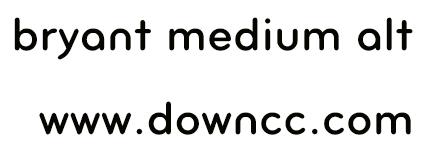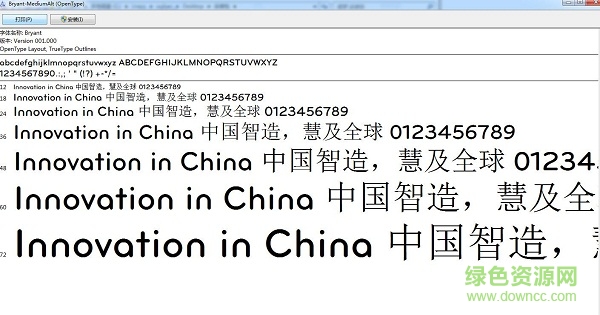
bryant medium字體
bryant medium alt字體是一款圓潤優(yōu)美的英文字體,結(jié)構(gòu)簡潔時(shí)尚,氣質(zhì)現(xiàn)代新潮,可用在各類報(bào)紙、雜志標(biāo)題、包裝設(shè)計(jì)、廣播媒介等各大領(lǐng)域,歡迎大家免費(fèi)下載!
bryant medium字體